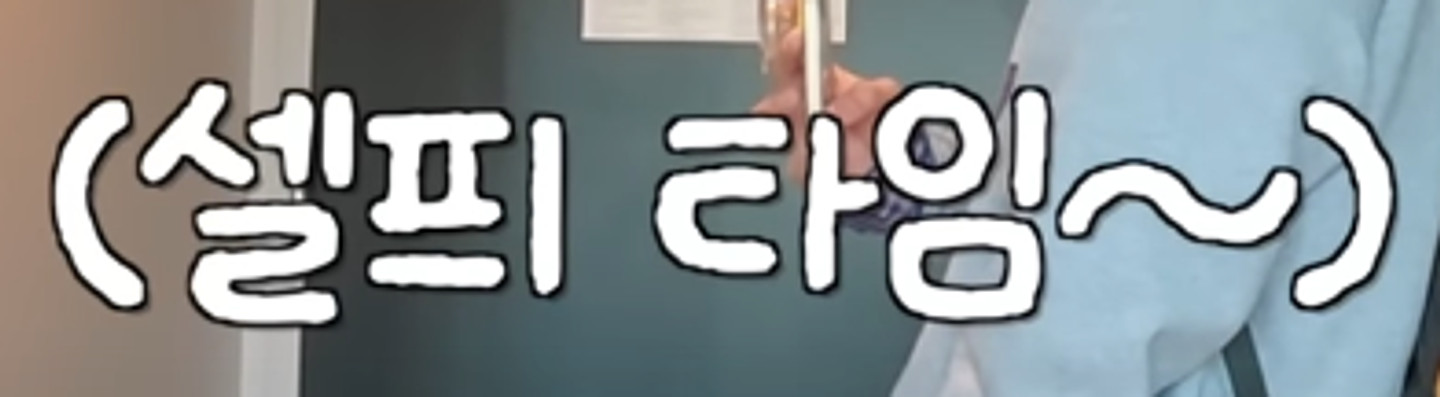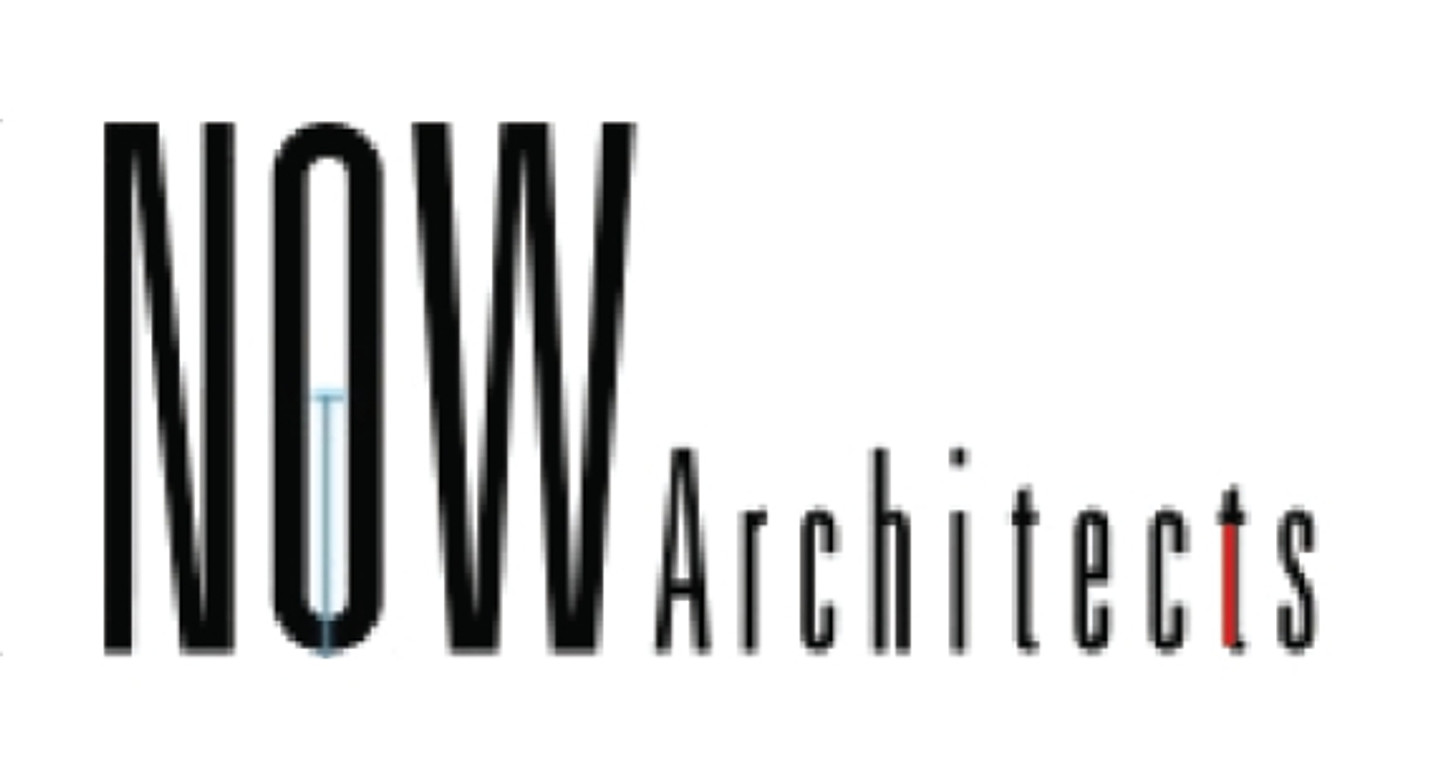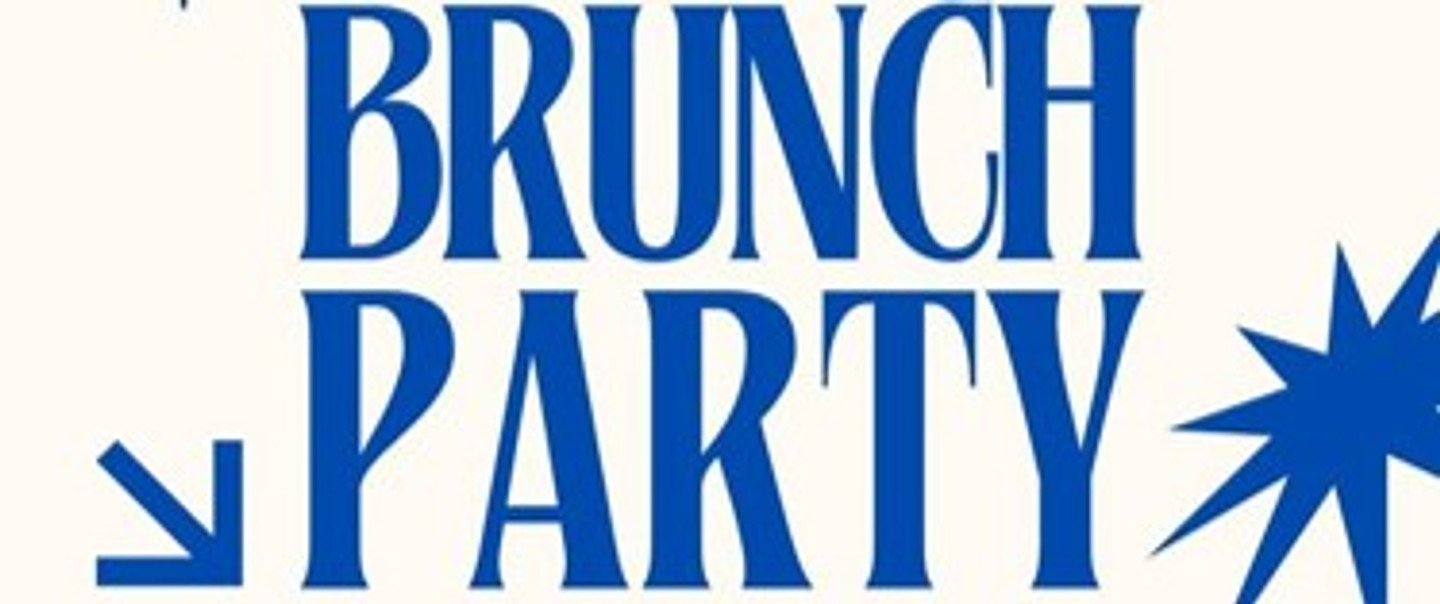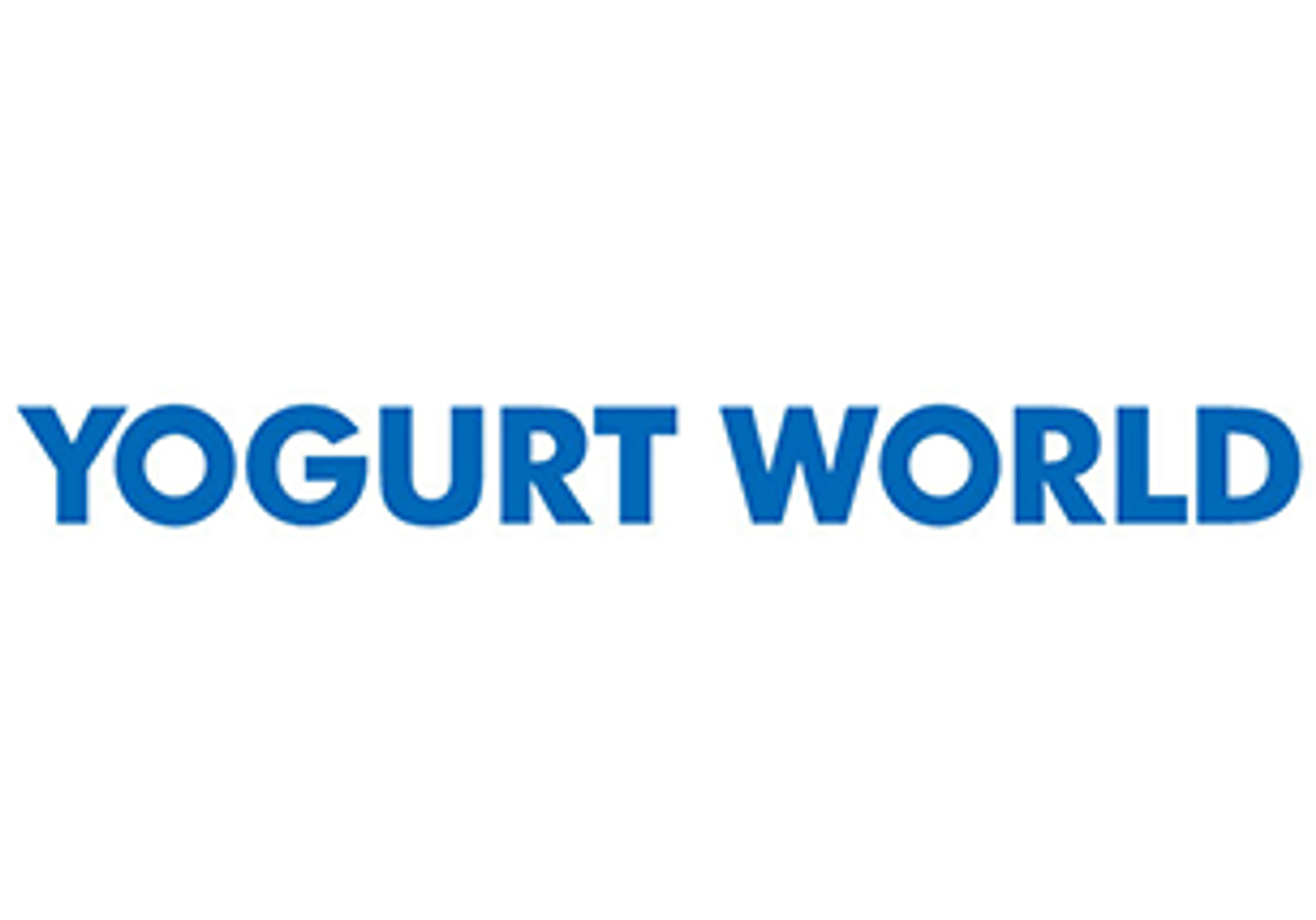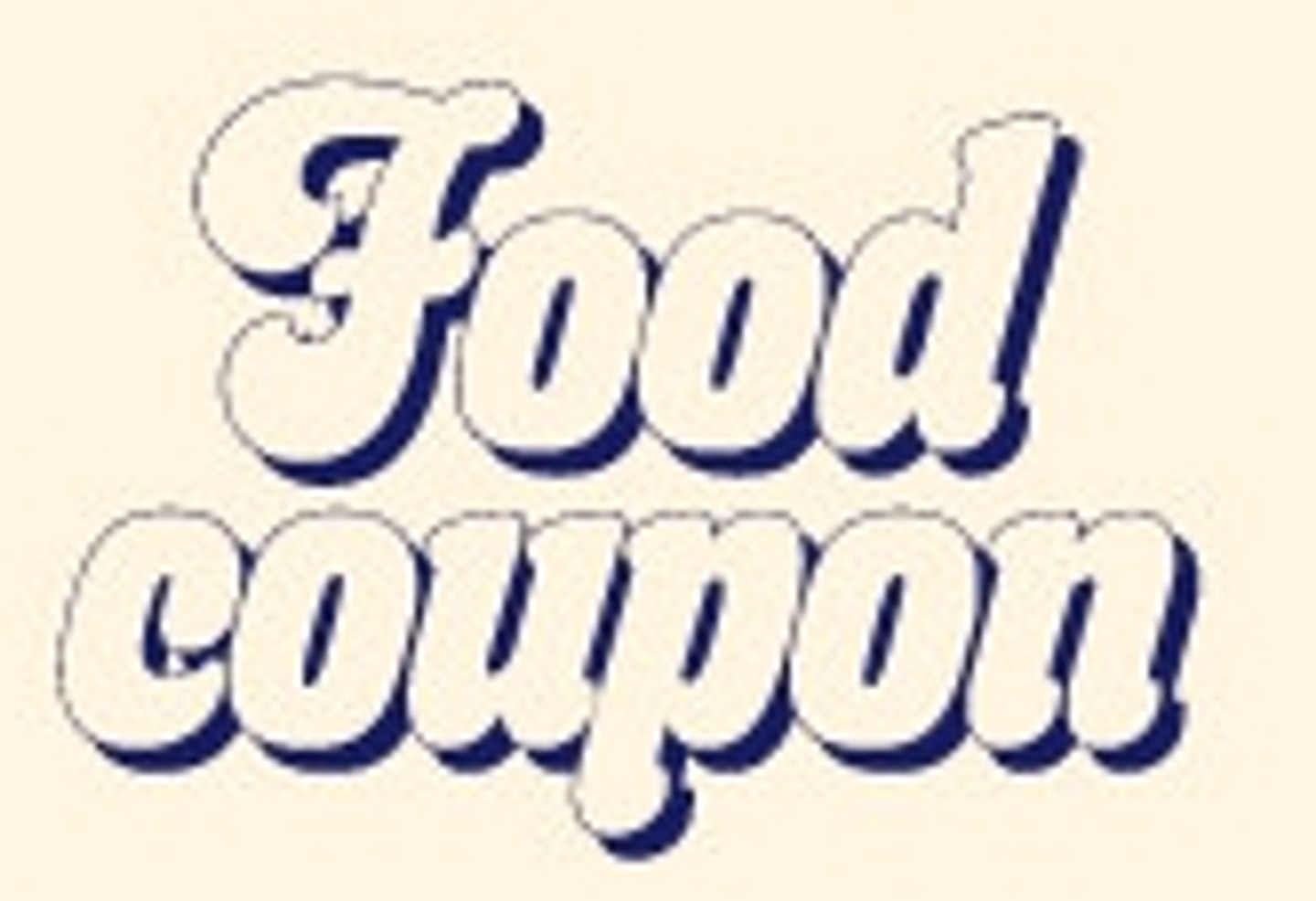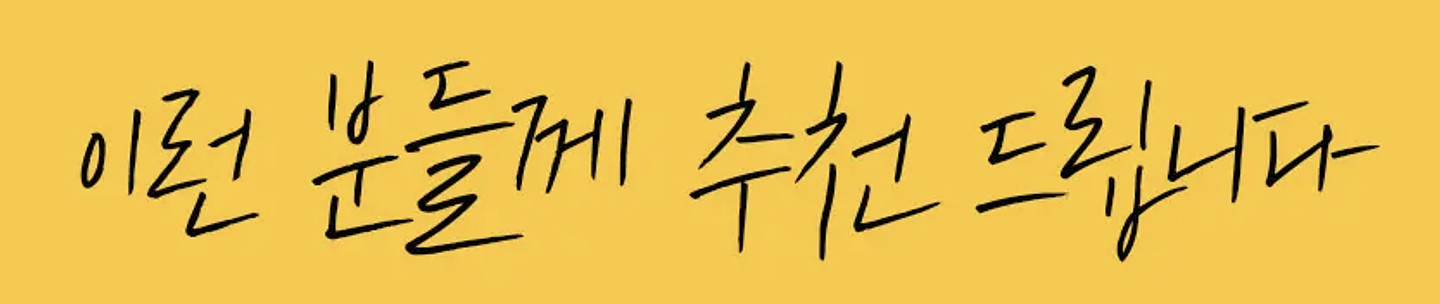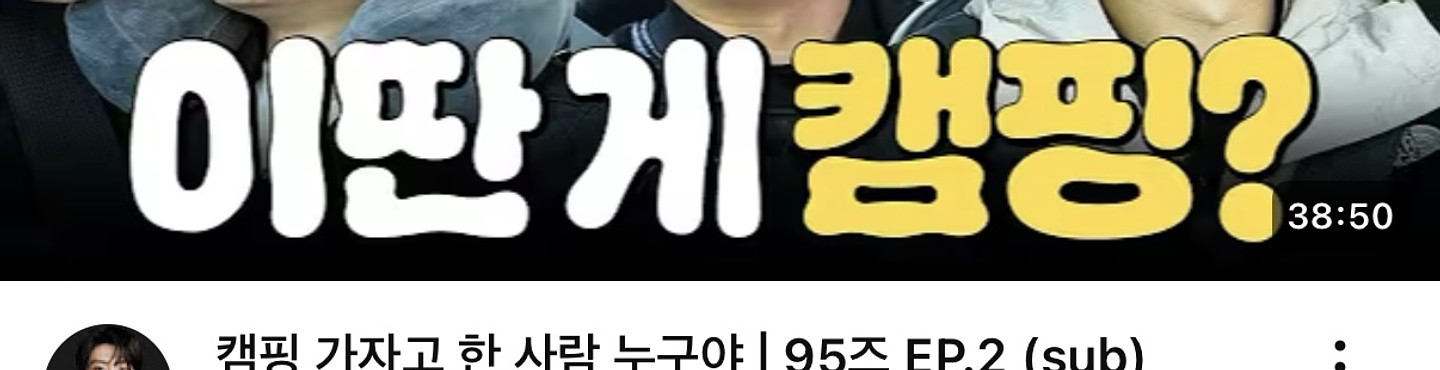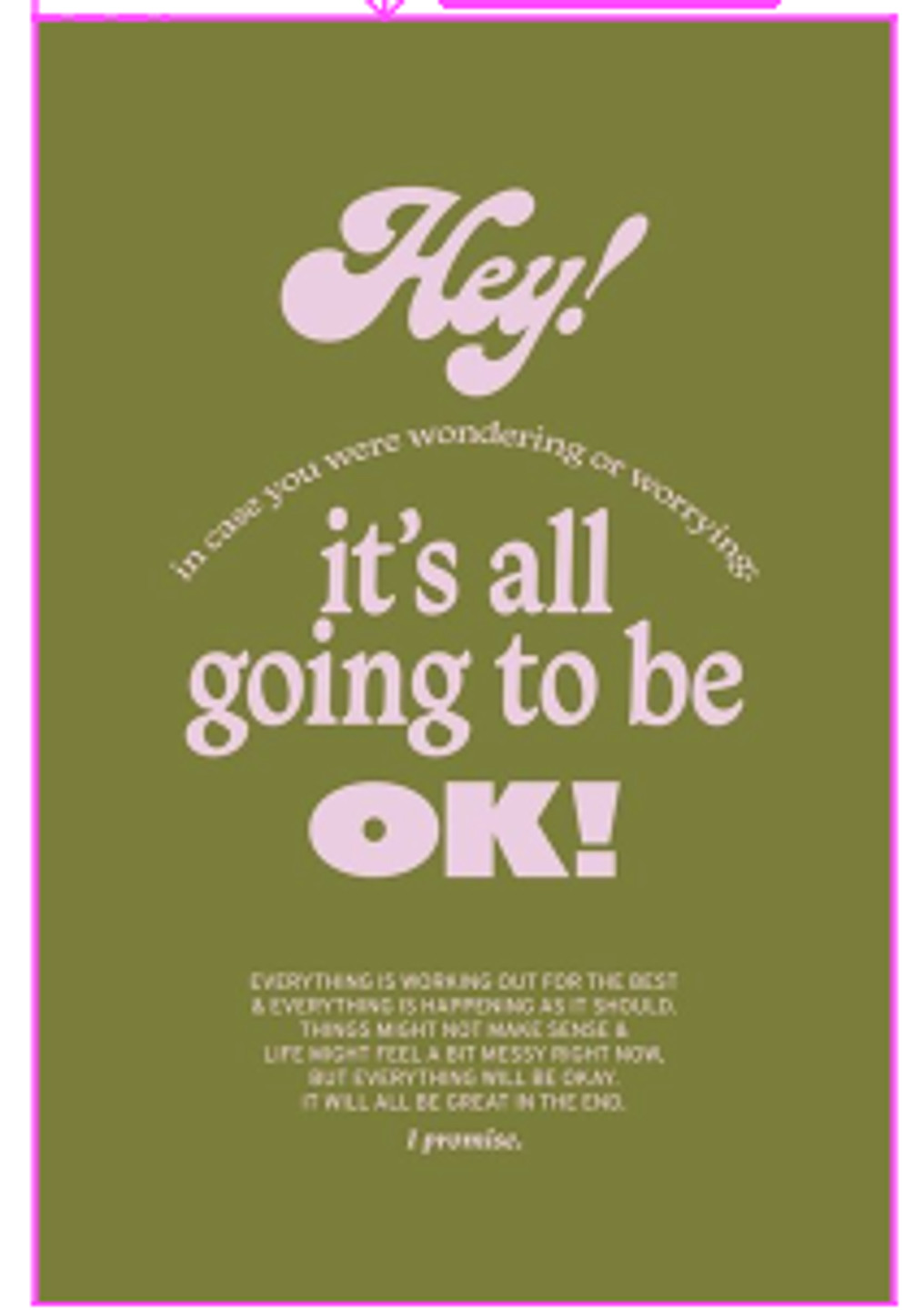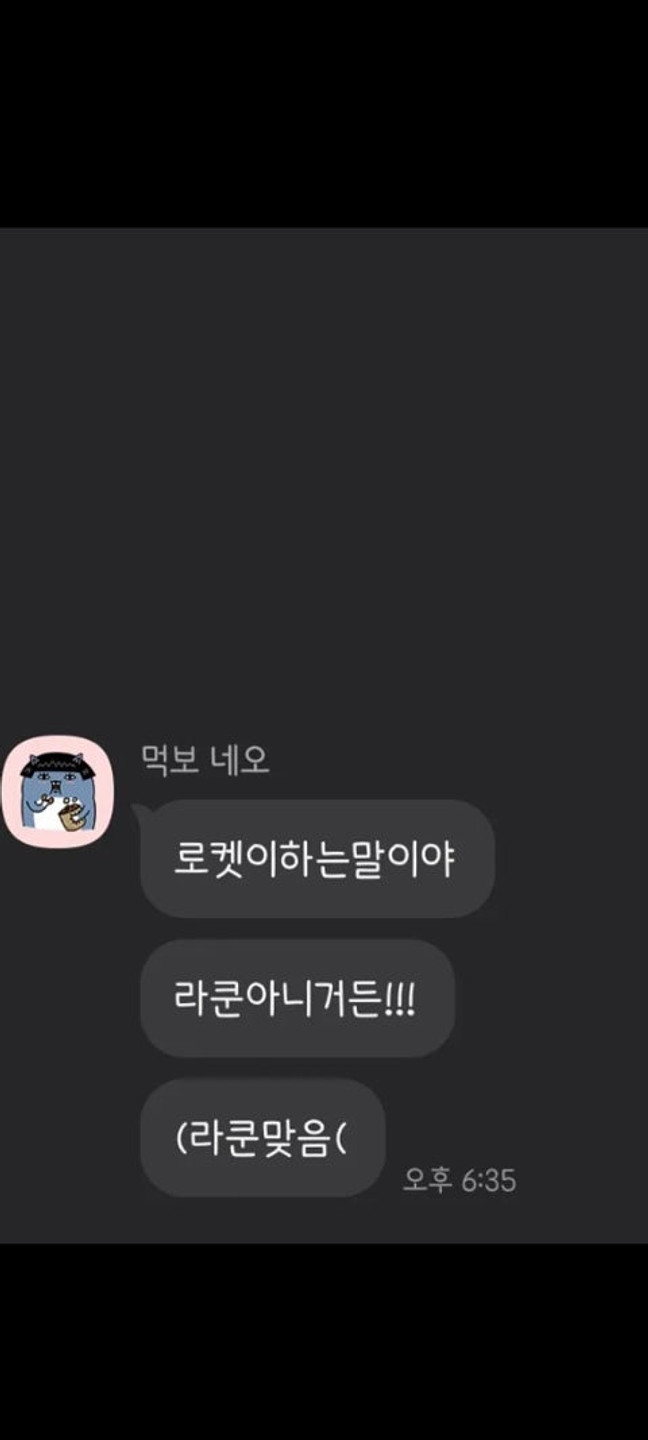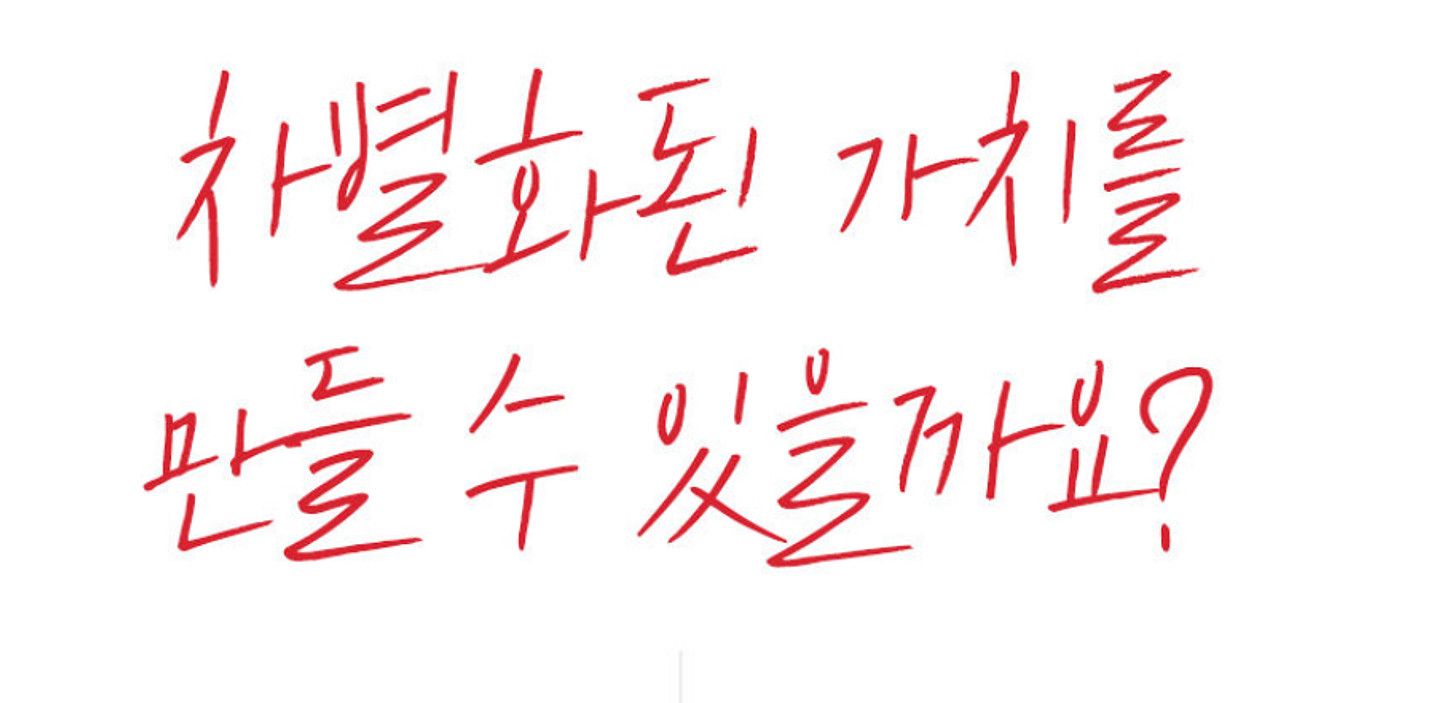
무한도전 자막 폰트인데 무슨 폰트인가요ㅜㅜ?
미드 가십걸에서 나온 폰트인데 ,, 폰트 이름 아시는 분 있으신가요?!
내 직장을 부탁해 랑 아래 말풍선에 사용된 폰트 각각 어떤걸까요?ㅠㅠ
폰트가 궁금합니다.
너무 깔끔하고 단정한 글씨체입니다. 전현무계획에 나온 글꼴입니다.
전현무계획에 나온 자막입니다. 너무 이뻐요.
캘리 글씨로 쓰면 너무 좋을 것 같은데... 손으로 쓴 걸까요?
무슨폰트예요?
https://www.youtube.com/shorts/qTWXpQ7zuf8 이채널 폰트인데 뭔지 궁금합니다!
유튜버 뿅글이님 채널에 자주 나오는 폰트 궁금해요!
무슨 폰트인지 알수있을까요?
무슨 자막일까요?
인스타 카드뉴스나 숏츠에 종종 이런 폰트가 뜨는데 무슨 폰트인가요?
효과자막
요건 무슨 폰트인가요~?!?
이거 어떤 폰트일까요 ㅠㅠ? 아무리 찾아도 모르겠어요
폰트 질문 드립니다. 귀여운 체의 폰트를 찾고 있는데 이미지 검색으로도 안 나오네요..ㅠ
인스타그램 메인로고에 'instagram' 사용된 폰트가 뭘까요?
이화여자대학교 대학원 논문 폰트인데요, 어떤 폰트인지 궁금합니다.
이 폰트는 뭘까요~? 도저히 못 찾겠어요 ㅠ.ㅠ
이 글씨체가 뭔지 궁금해요
찾아주세요
안녕하세요, 해당 글씨체가 무엇인가요?
무슨폰트인가여?
무슨 폰트일까요.?
’실시간 웨이팅 상황‘ 무슨 폰트일까요?
무슨 폰트일까요ㅠㅠㅠㅠㅠ?
여기 폰트 뭔가요? 귀엽게 생겨서 찾고 싶습니당
이런 자수에 들어가는 폰트는 뭘까요..? 그냥 궁서체인줄 알았는데 아니어서요.. ㅠㅠ..
어떤 폰트가체 일까요??
폰트명 알려주세요.
이 폰트 무엇인지 알 수 있을까요?
수산인의 날 기념식 문구의 폰트가 궁금합니다. 개별적으로 만든걸까요?
네이버 클립 채널에서 봤어요.
여기서 이 노란색 폰트 뭘까요?? 독특하고 예뻐서 꼭 알고 싶어요
바꾸자 김천! 여기 부분 폰트가 궁금합니다
이 폰트 뭔가요?! ㅜㅜ ㅇ자가 특이해서 너무 마음에 드는데 무슨 폰트인지 모르겠습니다
일본어폰트와 한국어 폰트가 궁금합니다ㅜㅜㅜ
토리든 포스터에 사용된 타이틀 폰트 아시는 분 있을까요
폰트 뭔지 궁금합니다
이거는 무슨 폰트일까요 ㅜㅜ
무슨 폰트인지 아신아ㅛ?
여기 영제로 'scenario sequence' 라고 쓰인 부분에 사용된 영문 폰트가 뭔지 알 수 있을까요? ㅠㅠ
온글잎 폰트라는데 무슨 폰트인지 알 수 있을까요?
온글잎 폰트라는데 무슨 폰트인지 알 수 있을까요??
트위터에서 봤는데 무슨폰트인지 궁금합니다
어떤 폰트인지 궁금해요!
무슨 폰트일까요? 심야괴담회에 나온 폰트
이 폰트 뭘까요?!